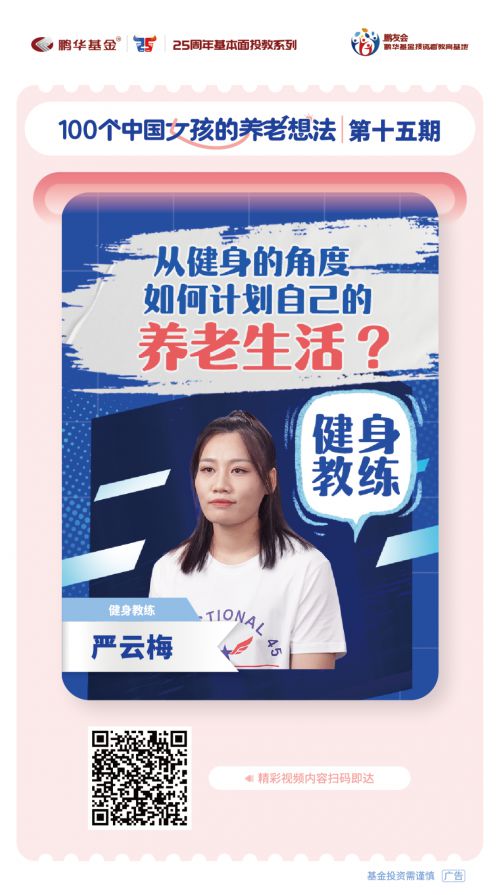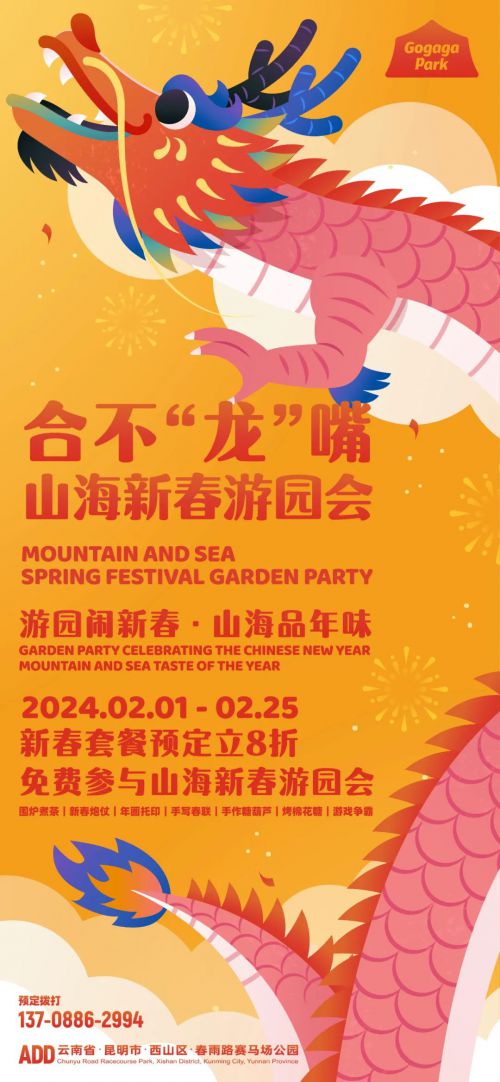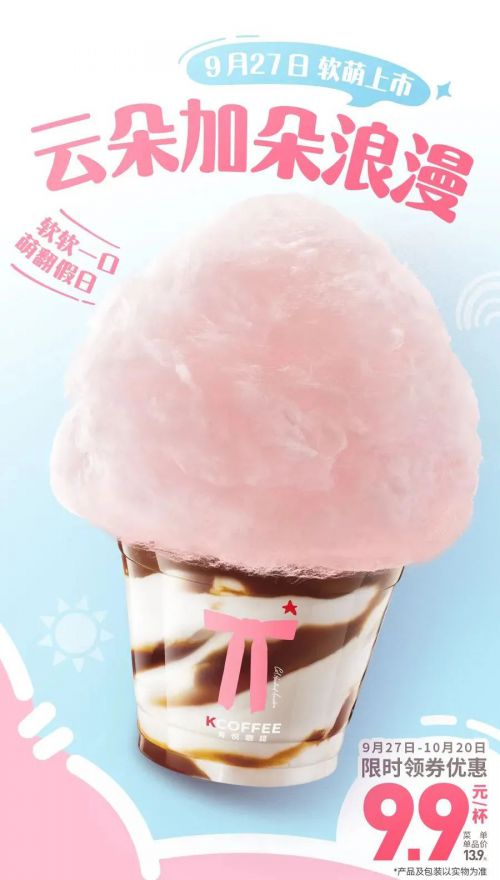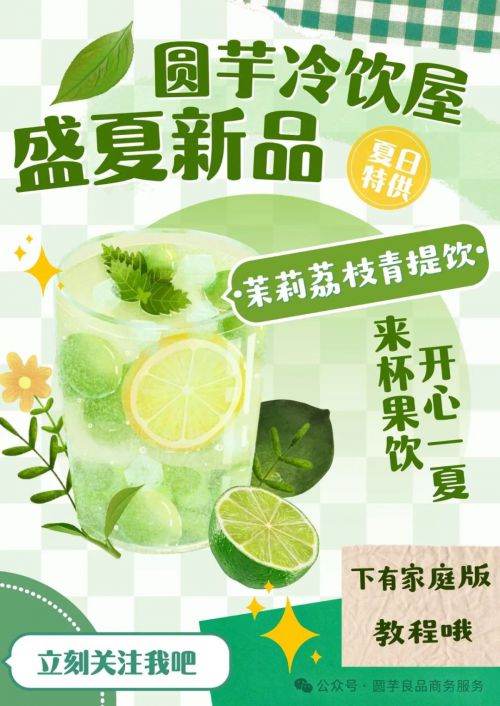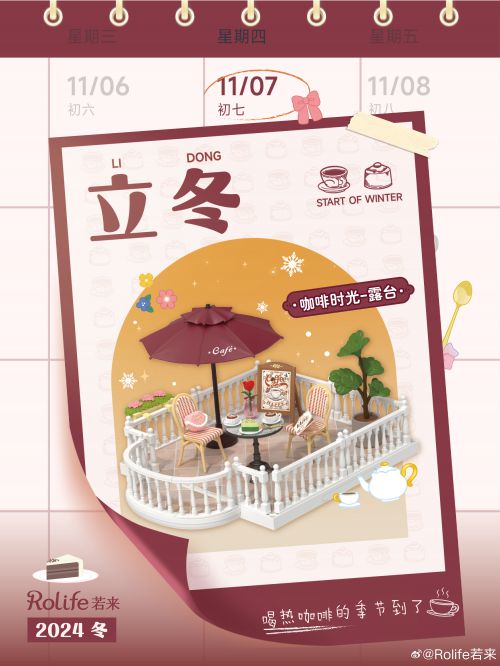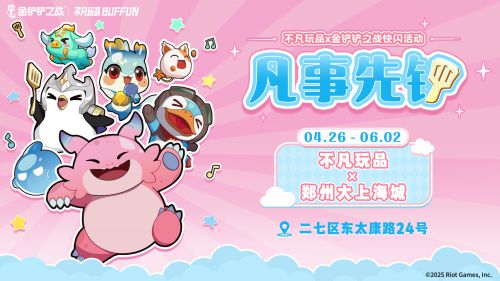
点字柔润
点字柔润是点字库推出的一款创意字体,支持简体中文常规字符集,适用于会员商用授权场景。字体以“柔润”为设计核心,整体采用扁宽字形,中宫宽博且字体重心居中,结构端正稳重,兼具端庄与灵动气质。 点字柔润的笔画设计充满巧思:线条粗细均匀,搭配圆头笔型与全字圆角处理,弱化了传统字体的硬朗感,让每一笔都透着柔美细腻。笔画间保持自然断开的连接关系,既保证文字识别清晰,又通过微妙的间距营造出轻松呼吸感,传递出温和亲切的视觉温度。无论是标题设计、包装文案还是品牌宣传,这款字体都能以有趣又优雅的风格,平衡创意表达与情感传递,成为传递温暖舒适氛围的理想选择。
卢鑫亚
90后字体设计师,曾获第二届字体之星评委奖,最具商业潜力奖,第三届字体之星评委奖。